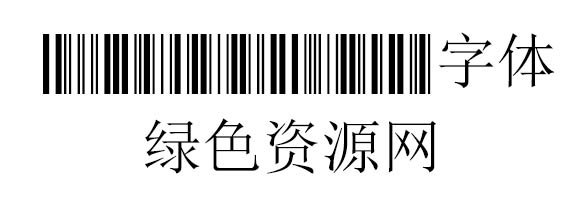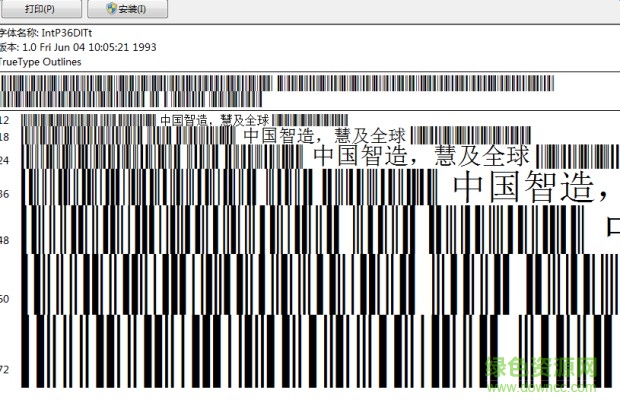
IntP36DlTt字體是條形碼字體庫(kù)中的一款個(gè)性字體,可應(yīng)用于廣告計(jì)、藝術(shù)創(chuàng)作、平面設(shè)計(jì)、印刷包裝等領(lǐng)域,喜歡的朋友可到綠色資源網(wǎng)免費(fèi)下載收藏。
IntP36DlTt字體是一種獨(dú)特的條形碼字體,它會(huì)將數(shù)字字母以條形碼的方式呈現(xiàn)給用戶